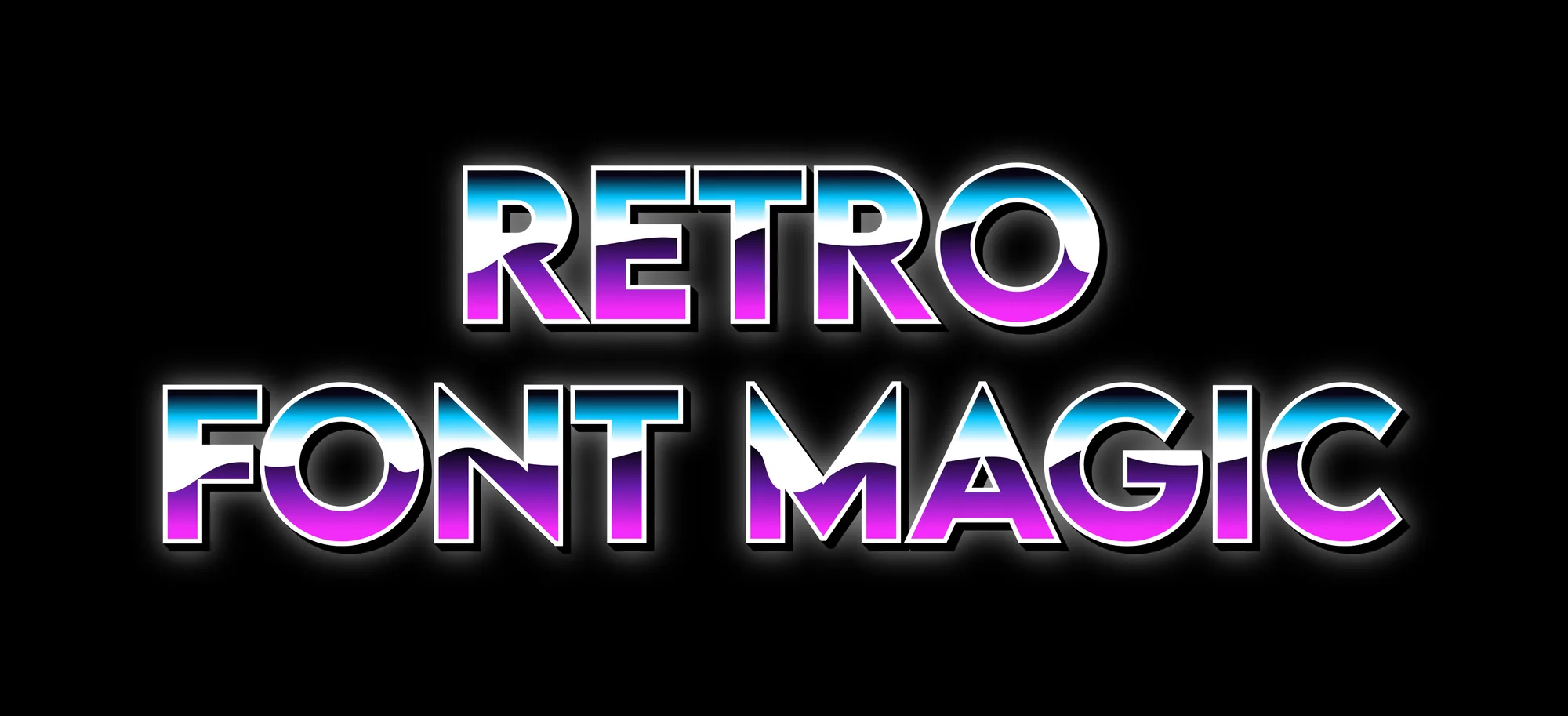
Ретро- и винтажные шрифты привносят в любой дизайн ностальгию, лёгкость и яркий характер. От пузатых букв в стиле 70-х до элегантной типографики середины века — эти стили напоминают о плакатах, виниловых пластинках и красочной рекламе прошлого. Давайте разберёмся, как использовать ретро-шрифты и винтажные текстовые эффекты, чтобы ваши работы выделялись.
Что делает шрифт ретро
Ретро-шрифт часто отличается округлыми формами, плотными изгибами или игривыми волнами, которые передают энергию 60-х и 70-х годов. Такие начертания выглядят тёплыми и словно созданными вручную — они идеально подходят для плакатов, футболок или брендинга, которому нужна нотка веселья и ностальгии. Попробуйте ретро-эффект для текста с мягкими градиентами или выцветшими оттенками, чтобы мгновенно добиться винтажного вида.
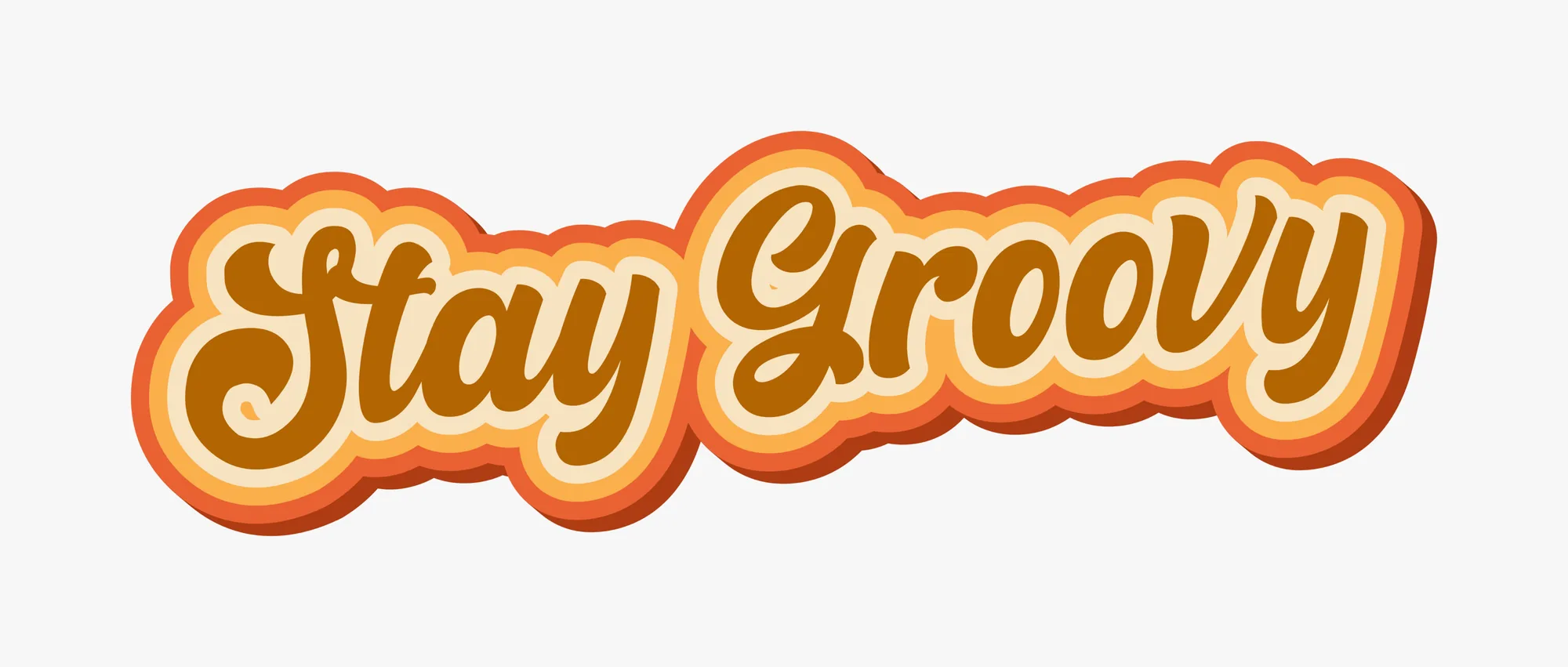
Винтажные шрифты с классическим шармом
Винтажные шрифты добавляют элегантности и вневременной красоты. Вспомните начертания со старых вывесок, открыток или киноафиш. Винтажный шрифт прекрасно подойдёт для свадебных приглашений, логотипов кафе или минималистичного ретро-брендинга. Сочетайте золотистые или сепийные тона с лёгкими тенями, чтобы текст выглядел подлинным и утончённым.
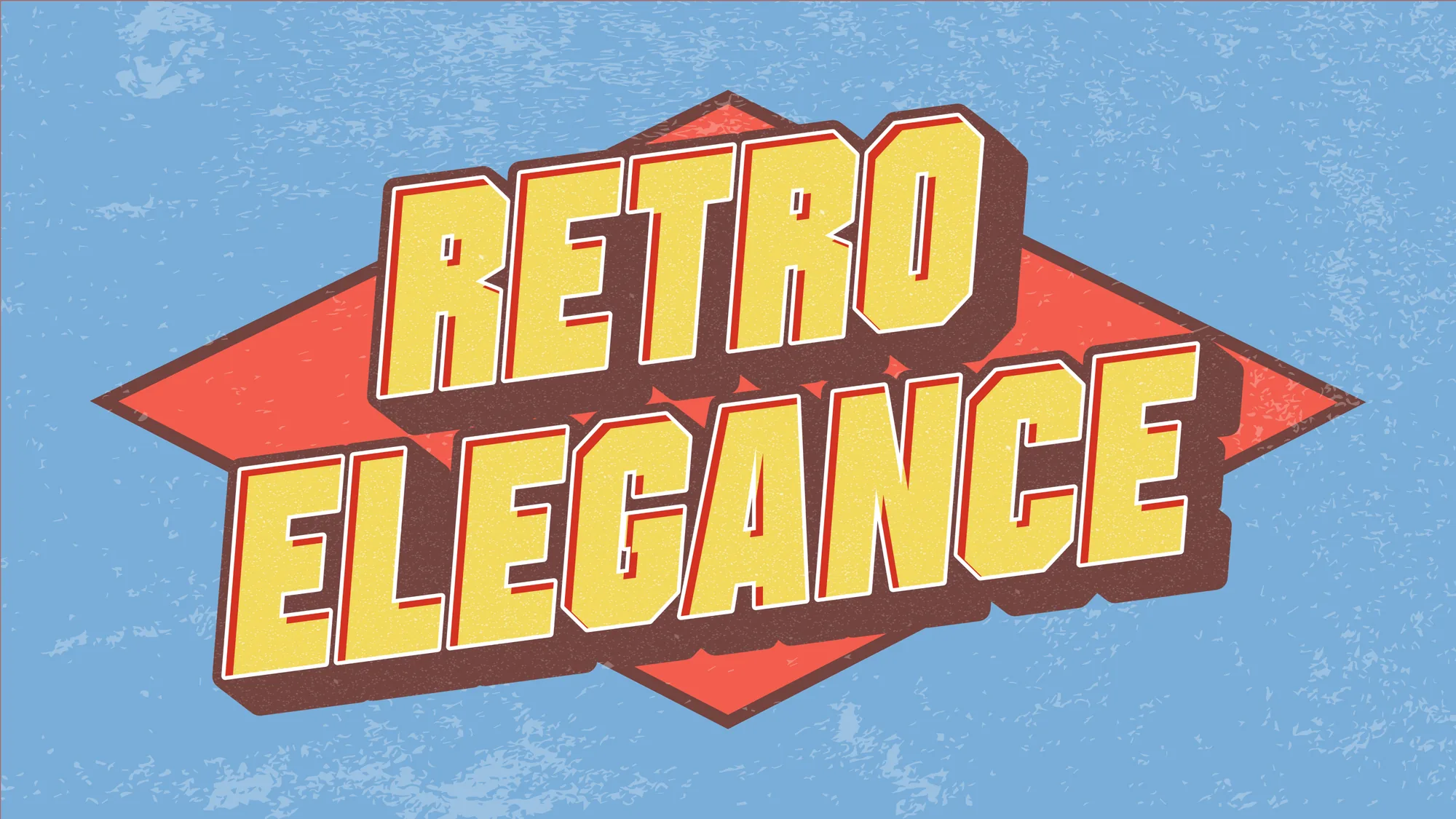
Грувовая и игривая типографика
Грувовые шрифты полны жизни — округлые, пузатые и будто в движении. Эти грувовые стили текста идеально подходят для ярких и весёлых дизайнов: постеров для фестивалей или визуалов для соцсетей. Смешивайте пастельные цвета, мягкие тени и волнистые формы, чтобы поймать безошибочно узнаваемую атмосферу 70-х.
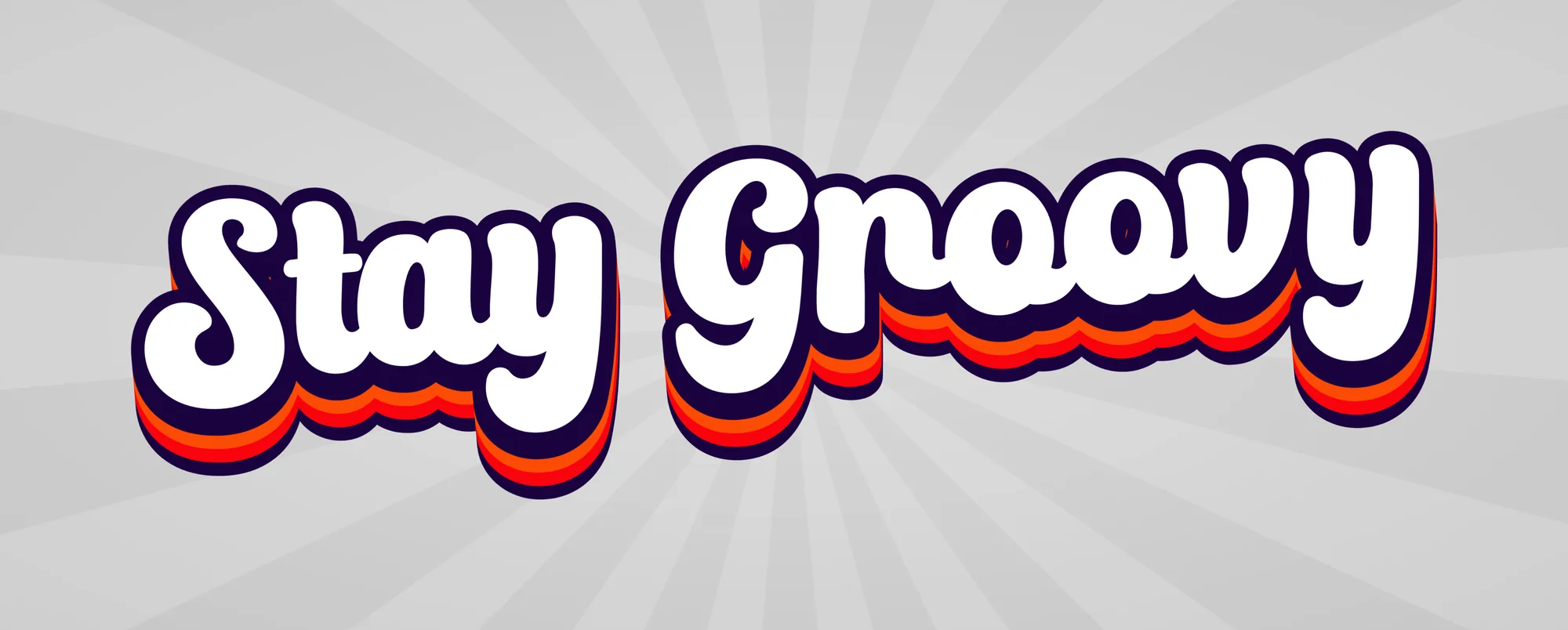
Современное ретро-вдохновение
Ретро — это не только о прошлом: это стиль, который соединяет олдскульный шарм с современным творчеством. Сегодня дизайнеры используют ретро-шрифты смело и по-новому, сочетая яркие градиенты, многослойные текстуры и 3D-эффекты. Создаёте ли вы логотип, обложку альбома или постер с цитатой — ретро-типографика добавит характера и эмоций. Игровые логотипы держатся на том же чувстве: толстые красные буквы с белой обводкой, которые игроки до сих пор называют классикой, остаются чистым ретро-дизайном. Наше руководство по шрифтам Roblox показывает, как его воссоздать.
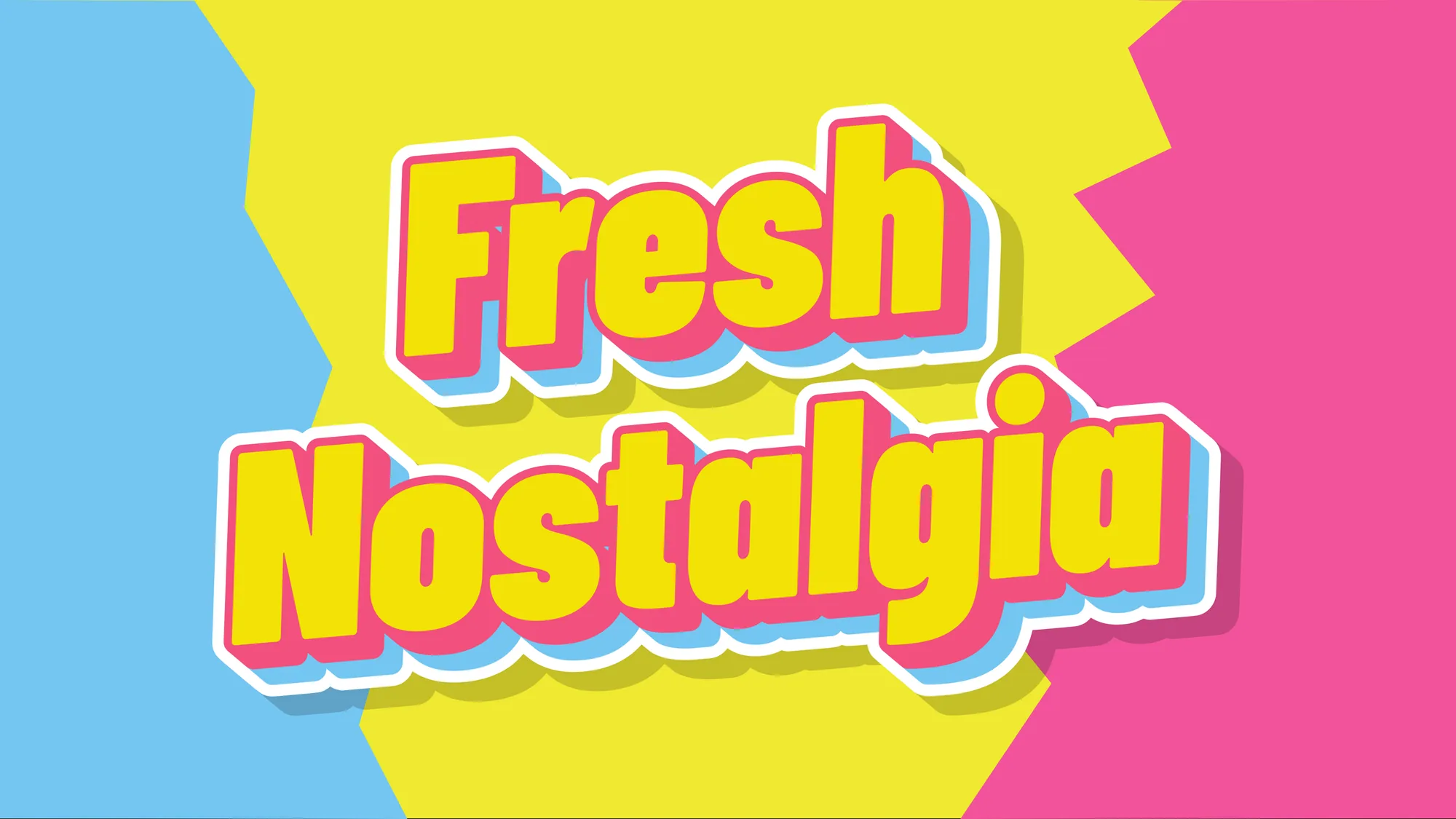
Заключение